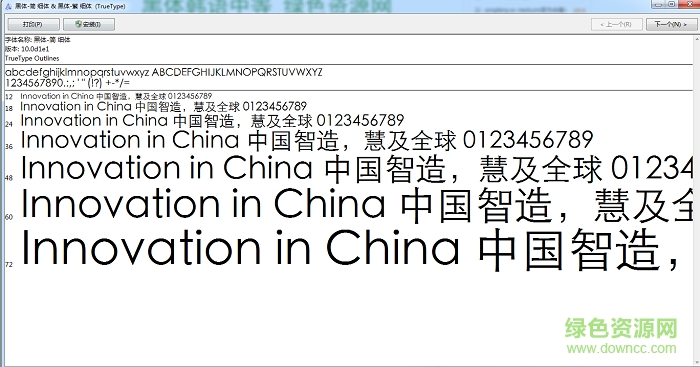
黑體 簡(jiǎn) 細(xì)體字體是一款纖細(xì)的中文廣告字體,線(xiàn)條柔軟流暢,字形簡(jiǎn)潔明快,結(jié)構(gòu)嚴(yán)謹(jǐn)勻稱(chēng),這款字體從外形上看雖然不夠精美卻十分實(shí)用,有需要者快來(lái)綠色資源網(wǎng)下載吧!
黑體字是現(xiàn)代漢字體系中最重要的字體之一。尤其是隨著20 世紀(jì)末電腦和互聯(lián)網(wǎng)的普及,黑體字的價(jià)值得到了進(jìn)一步體現(xiàn),它簡(jiǎn)潔的筆畫(huà)特征與屏顯介質(zhì)特性相符,從而成為了當(dāng)今各種屏幕媒介中最有發(fā)展前景的字體。
粗黑、超粗黑(特黑)、大黑、細(xì)黑、美黑、宋黑、水黑、藝黑、氈筆黑、平黑等類(lèi)型。